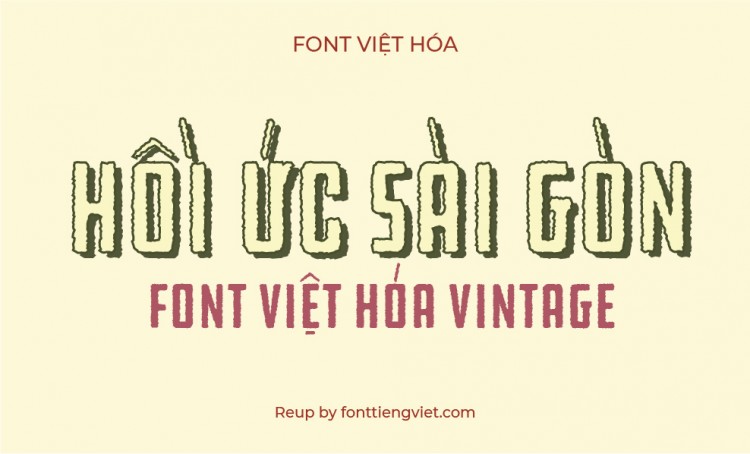
Font việt hóa iCiel BCDDC Hardware Rough ( Font vintage retro ) – Vẻ đẹp hoài cổ ấn tượng
Giới thiệu về Font việt hóa iCiel BCDDC Hardware Rough ( Font vintage retro )
Trong thế giới thiết kế đồ họa hiện đại, việc tìm kiếm một bộ Font Chữ mang đậm hơi thở cổ điển nhưng vẫn đảm bảo tính ứng dụng cao là điều vô cùng quan trọng. Font việt hóa iCiel BCDDC Hardware Rough ( Font vintage retro ) chính là giải pháp hoàn hảo cho những ai yêu thích phong cách hoài niệm. Đây là một bộ font được lấy cảm hứng từ các bảng hiệu cơ khí cũ và bao bì công nghiệp thế kỷ trước. Với những đường nét thô mộc, hiệu ứng nhám (rough) đặc trưng, bộ font này giúp các tác phẩm thiết kế trở nên có chiều sâu và cá tính hơn bao giờ hết.
Đặc điểm nổi bật của bộ font vintage
Điểm thu hút nhất của Font việt hóa iCiel BCDDC Hardware Rough ( Font vintage retro ) nằm ở các góc cạnh được xử lý tinh tế để tạo cảm giác cũ kỹ tự nhiên. Bộ font hỗ trợ đầy đủ tiếng Việt giúp các nhà thiết kế tại Việt Nam dễ dàng triển khai trên nhiều nền tảng khác nhau mà không lo lỗi font hay thiếu ký tự đặc biệt.
Ứng dụng Font việt hóa iCiel BCDDC Hardware Rough ( Font vintage retro ) trong giáo dục và thiết kế
Bộ font này không chỉ dành cho các dự án thương mại mà còn rất phù hợp trong môi trường giáo dục. Giáo viên và học sinh có thể sử dụng Font việt hóa iCiel BCDDC Hardware Rough ( Font vintage retro ) để làm nổi bật các tiêu đề trên báo tường, bìa sách hoặc các bài thuyết trình lịch sử. Sự kết hợp giữa nét chữ mạnh mẽ và phong cách retro giúp nội dung truyền tải trở nên sống động và thu hút sự chú ý của người xem một cách tự nhiên.
Cách sử dụng font hiệu quả
Để tối ưu hóa vẻ đẹp của font, bạn nên kết hợp với các tông màu trầm như nâu đất, vàng cũ hoặc xanh rêu. Việc sử dụng trong các ấn phẩm như menu quán cà phê, logo thương hiệu thủ công hay poster sự kiện sẽ tạo nên một tổng thể hài hòa và chuyên nghiệp.
Kết luận và trải nghiệm Font việt hóa iCiel BCDDC Hardware Rough ( Font vintage retro )
Sở hữu những ưu điểm vượt trội về thẩm mỹ, đây chắc chắn là lựa chọn không thể bỏ qua cho kho tài nguyên sáng tạo của bạn. Hãy bắt đầu nâng tầm dự án thiết kế ngay hôm nay với Font Miễn Phí, Font Việt Hóa, Font việt hóa iCiel BCDDC Hardware Rough ( Font vintage retro ) để cảm nhận sự khác biệt mà phong cách vintage mang lại.